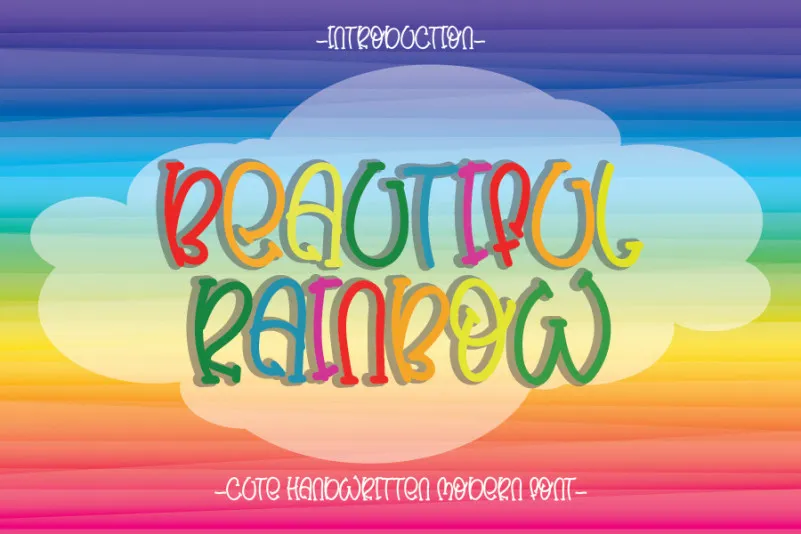
Beautiful Rainbow Font – Download Grátis
Esta fonte é uma mão-dura cheia de personalidade para projetos que precisam soar alegres e divertidos. Ideal para criações onde você quer transmitir uma sensação aconchegante e descontraída, ela se adapta perfeitamente para qualquer projeto de design. Seja em letras grandes ou pequenas, essa fonte mantém seu brilho especial e sua essência única que fará seus projetos realmente saírem do papel. A designer, handwrittenwanda, nos apresenta uma fonte pronta para ser usada em várias situações, desde cartões de aniversário até rótulos de embalagens. Ela está aqui para tornar cada ideia original que você tiver em um trabalho de arte real e memorável. Explore as infinitas variações dessa linda fonte e descubra como ela pode transformar seus projetos digitais em verdadeiros artistas, semelhante a uma pintura ou desenho. Sua caligrafia fresca e vibrante é o ideal para dar um toque especial aos seus trabalhos de design. Experimente-a hoje e veja qual projeto não ficará melhor com ela!